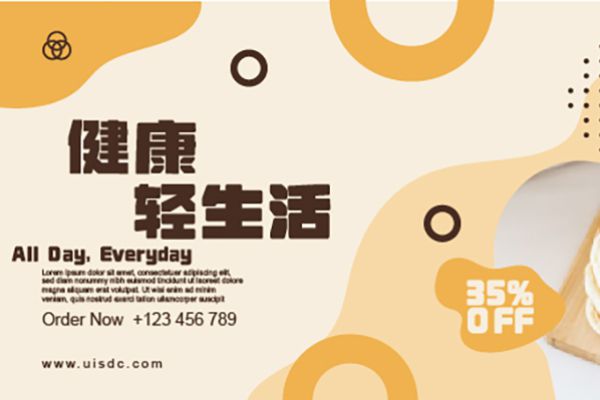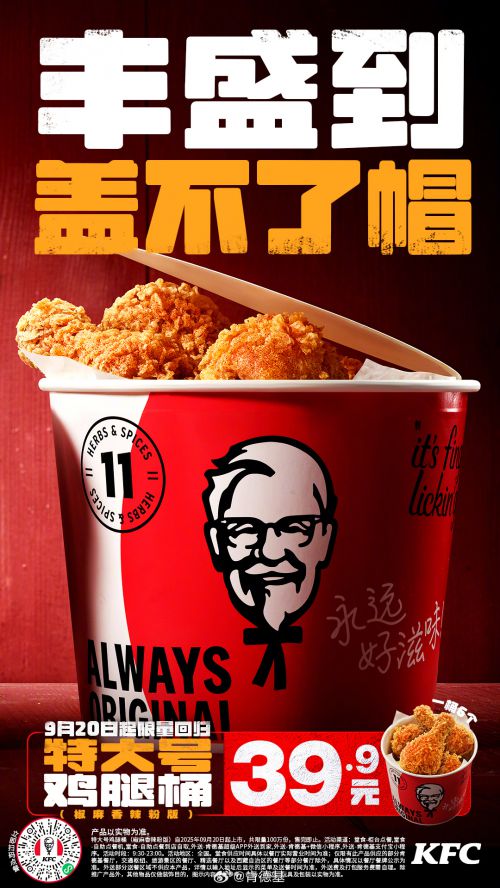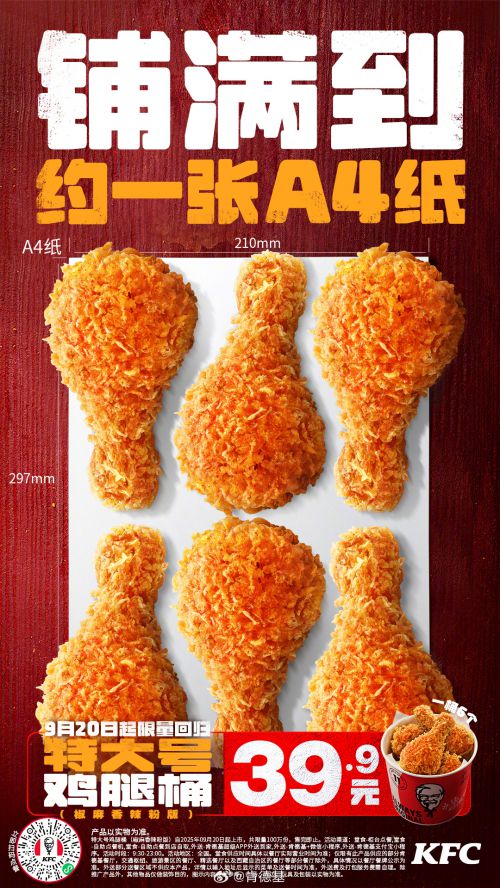
荆南缘默体
荆南缘默体是一款以力量风格为核心的创意字体,字形方正稳健,重心居中、中宫适中的结构设计,让字体在大气之余兼具平衡感,整体呈现出刚劲有力的视觉气质。 荆南缘默体在笔型细节上颇具巧思:斜切元素的融入为笔画增添锐利锋芒,方头笔画搭配断开式连接,既保留了利落的线条感,又通过笔画间隙形成独特节奏。粗且均匀的笔画线条,进一步强化了字体的力量属性,同时确保了文字的清晰识别度。作为支持免费商用的字体,荆南缘默体适用于标题设计、品牌标语、海报宣传等场景,为创意作品注入强劲的视觉张力。